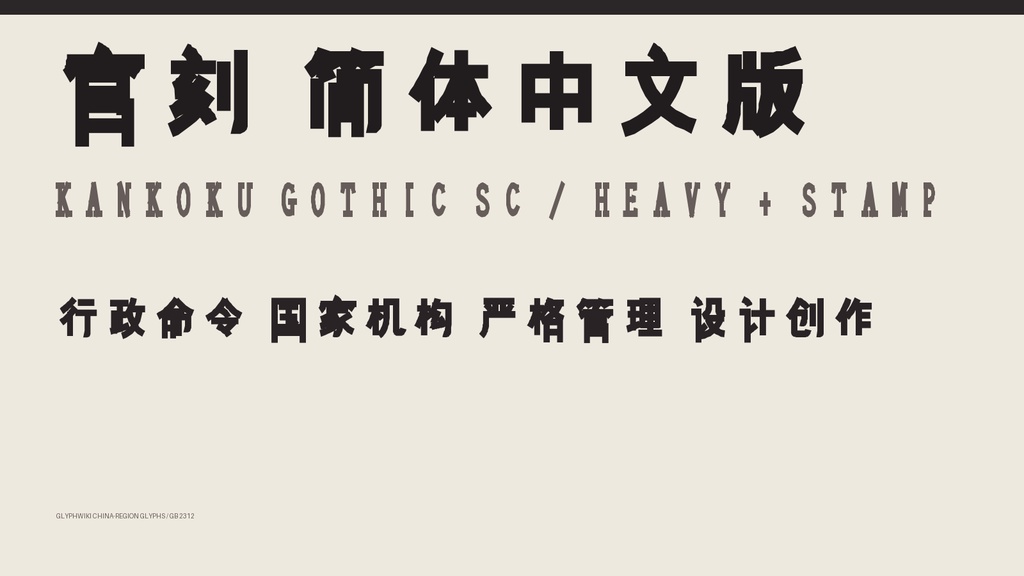
官刻黑体 SC|简体字6,763字・2款字体
【官刻黑体 SC / KANKOKU GOTHIC SC】 为架空行政机关、命令书、告示牌与配给票设计的硬质简体中文黑体。 纵长字面、均匀黑度与方格化轮廓,营造制度、秩序和旧式印刷的冷峻气氛。 Heavy 强调厚重而整齐的公文感,Stamp 则加入印章与粗糙油墨般的缺口。 ■ 价格 1,480日元 ■ 内含字体 ・Heavy:厚重、整齐、具有强制力的版本 ・Stamp:带有旧印刷和印章磨损感的版本 ■ 格式 TrueType(TTF)2款 / Windows・macOS ■ 收录 每款共7,542个字码(包含空格) GB 2312 全部汉字:6,763字 拉丁字母、数字、半角与全角符号:779个 ■ 特点 ・纵长字面与统一黑度 ・硬直方格轮廓和行政标牌般的压迫感 ・汉字、英文字母、数字和符号保持一致的制度化造型 ・Heavy / Stamp 两种印象 ■ 推荐用途 反乌托邦游戏、架空公文、警告标识、电影道具、TRPG资料、海报、视频标题、直播画面与标志 ■ 使用许可 可用于个人及商业项目。可用于标志、视频、游戏、印刷品、直播素材、同人及商业作品。 无需署名。禁止重新分发、共享或转售字体文件。 详细条款请查看ZIP内的使用许可。 ※本字体为虚构世界观设计,与现实中的国家、军队或政治组织无关。